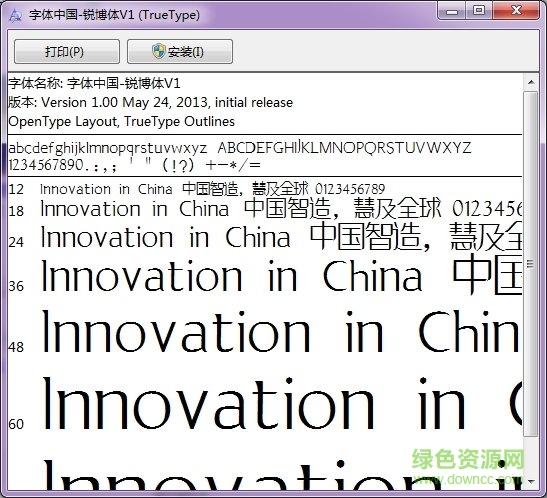
銳博字體是字體中國推出的一款細(xì)線中文系,纖細(xì)的造型讓字體顯得大方的體,本系列有v1和v2兩款字體,歡迎大家下載嘗試!
銳博體字體方中帶圓,筆畫 柔美光潔、粗細(xì)均勻、結(jié)構(gòu)美觀。可用于廣告設(shè)計字體、網(wǎng)頁設(shè)計字體、包裝設(shè)計字體、 屏幕顯示字體等。